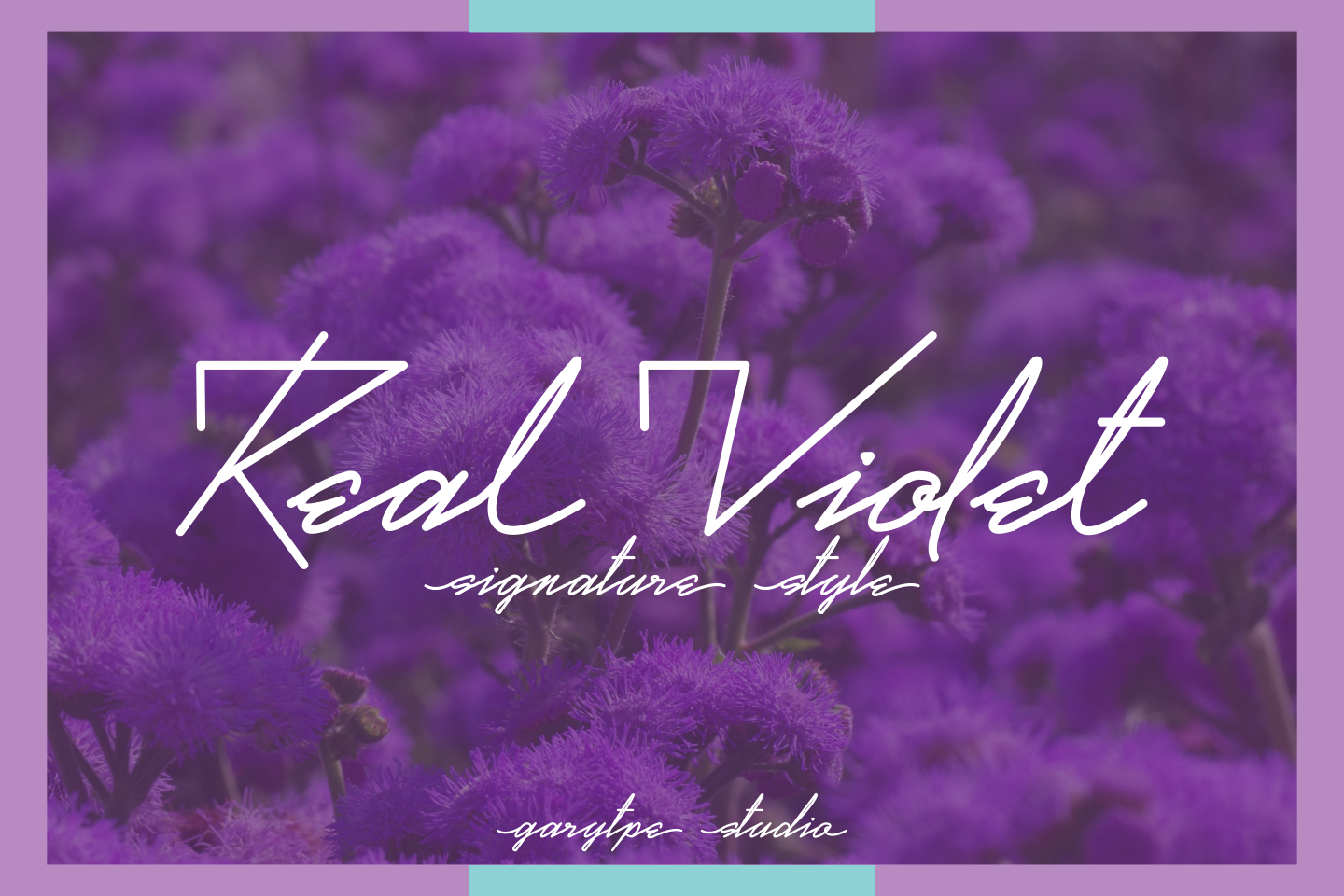
Real Violet Handwritten Font – Download Grátis
Introduzimos Real Violet, uma nova coleção de fóntes de escrita simbólica que traz o encanto único dos autênticos traços vivos. Inspirada por uma vida elegante e perfeita, esta família de letras foi projetada para abrangência ampla. Real Violet é ideal para aplicações variadas como mooboard, casamentos, citações privadas para assinaturas, marcas d’água, logotipos, panfletos, cartazes, folhas de endereço e roupas. Real Violet é mais do que um simples complemento de texto; ela se encaixa perfeitamente em uma variedade de projetos. Seja para adicionar um toque a seu projeto de blog, criar cartões personalizados ou até mesmo imprimir suas citações favoritas na parte traseira dos seus sapatos (ainda que este último não seja oficialmente recomendado), Real Violet está pronta para ajudá-lo. Esta fonte é perfeita tanto para designers como para aqueles que criam em casa. Suas linhas suaves e traços curvos oferecem uma aparência elegante e única, tornando-a o ideal para criar um ambiente especial e memorável nos seus projetos. Seja para qualquer ocasião ou projeto de design, Real Violet está aqui para ajudá-lo a expressar seu estilo de maneira autêntica e inconfundível.